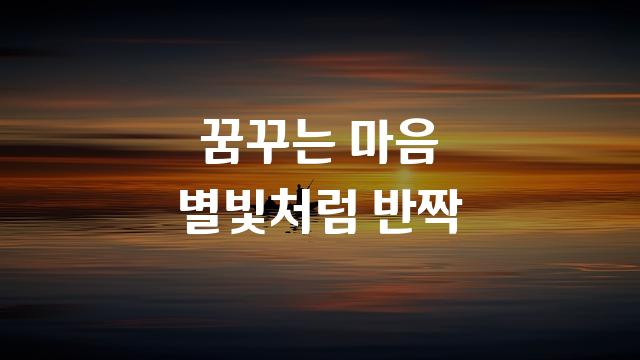
엄마까투리체는 귀여움과 따스함을 담은 두꺼운 둥근 손글씨 폰트입니다. 안동시에서 제작하여 감성적인 터치와 친근감을 더해 줍니다.
엄마까투리체은(는)
단단함, 부드러움, 복실복실, 둥근 스타일, 감성적인, 굵은 고딕, 두꺼운 스타일, 귀여운 스타일, 손글씨 계열의 생김새를 가지고 있으며
교육 자료, 인사말 카드, 어린이 책 등에서 자주 활용되며, 효과적인 메시지 전달에 적합합니다.
이 폰트는 교육, 라이프스타일, 유아/가족 분야에 잘 어울리며,
편안한, 귀여운, 친근한 느낌을 담고 있는 것이 특징입니다.